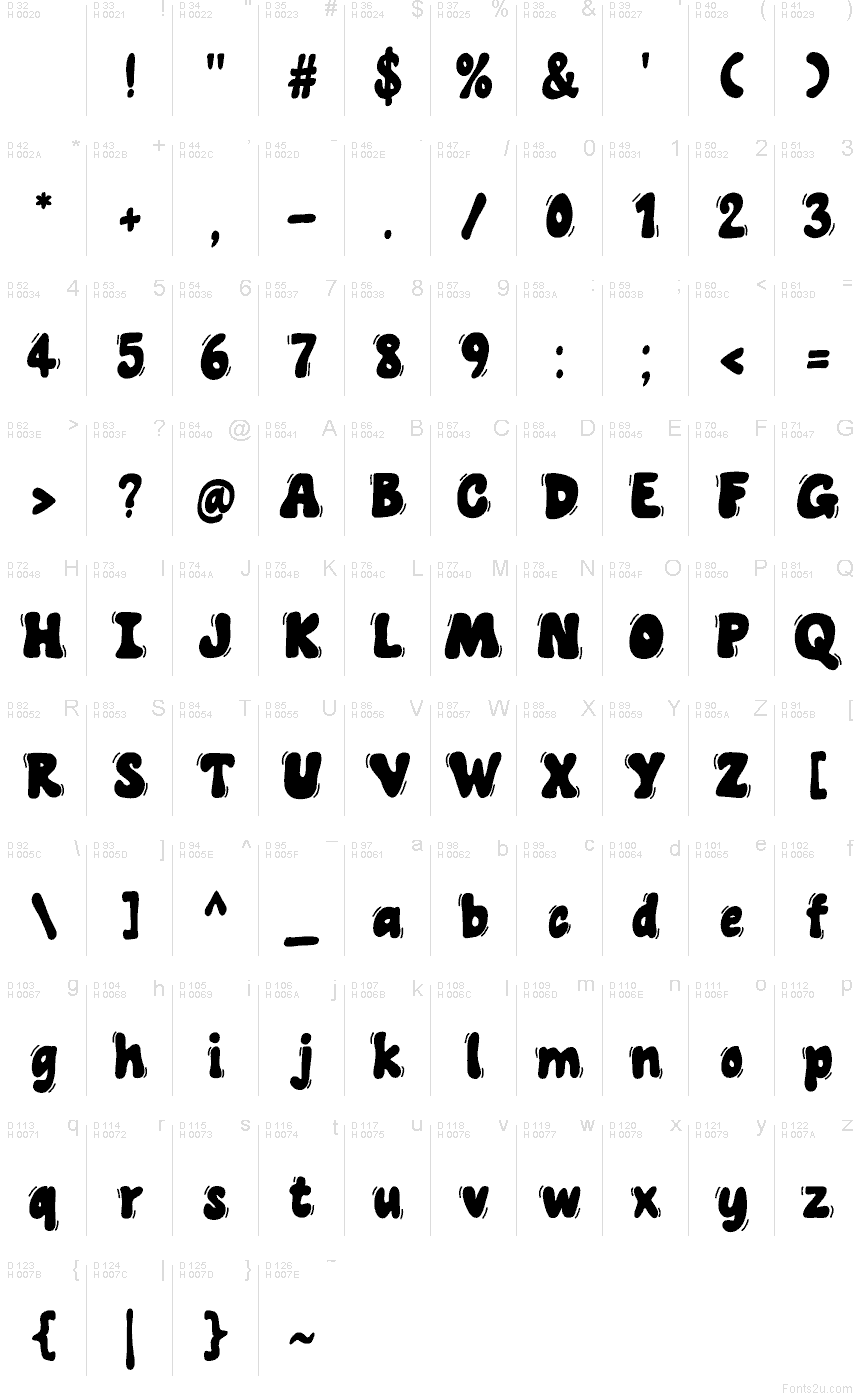
Шрифт Shake Alone від Hello Good Studio - це безкоштовний дисплейний шрифт у мультяшному стилі з округлими, намальованими від руки формами та м'якими, нерівними краями. Літери виглядають «пухкими» та невимушеними, а невеликі вигини й неправильні лінії роблять міжлітерні інтервали живими, але при цьому охайними.
Shake Alone чудово підходить для дитячих плакатів, пакування снеків, логотипів, графіки для соціальних мереж та стікерів. Цей безкоштовний шрифт також добре пасує для заголовків і коротких промо-текстів, коли вам потрібен дружній, неформальний тон із ноткою грайливості.